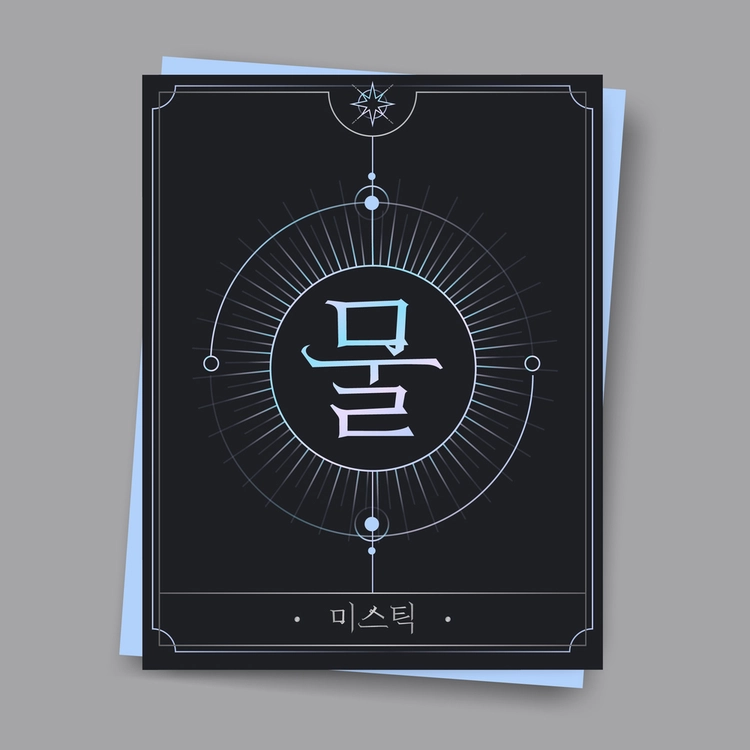
저희가 알고 있던 명조체는 부드러운 느낌을 기반으로 섬세함과 감성적인 느낌을 주고 있습니다. 이러한 느낌을 주는 명조체 베이스에 각진 부리(세리프)와 견고한 획의 전개를 적용하여 미스틱문 폰트가 탄생하였습니다. 정갈하면서 입체적인 디자인포인트가 돋보이는 새로운 형태의 명조체를 만나보세요.